Namen eintippen, Stil wählen, PNG herunterladen. Das ist alles, und es dauert etwa zehn Sekunden.
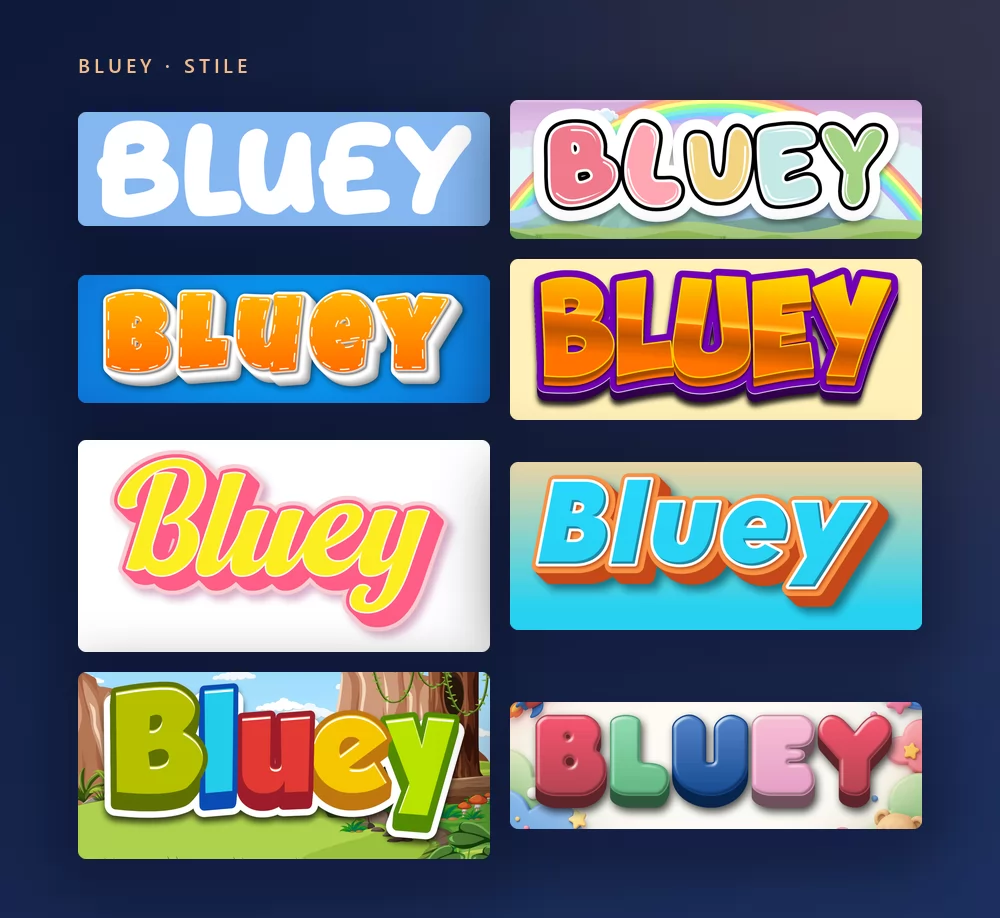
Alle stammen aus demselben Bluey-Schriftgenerator, nur mit einem anderen Stil aus der Liste. Nichts zu installieren, kein Konto.
Über die Bluey-Schrift
Bluey ist eine australische Zeichentrickserie für Vorschulkinder, erdacht von Joe Brumm und produziert von Ludo Studio in Brisbane. Sie lief 2018 zuerst auf ABC Kids und ging über BBC Studios und Disney+ um die Welt. Sie folgt Bluey, einem sechsjährigen Blue-Heeler-Welpen, ihrer kleinen Schwester Bingo und den Eltern Bandit und Chilli durch Fantasiespiele, die den zuschauenden Erwachsenen jedes Mal eine Lebensweisheit unterjubeln.
Das Logo der Serie ist ein eigens gezeichneter Schriftzug: dicke, runde, hüpfende Versalien, die für die Sendung entworfen und nie als Schrift veröffentlicht wurden. Die Schrift für alles andere, die Titelkarte, den Abspann und die offizielle Website, ist Hello Headline, entworfen von Veneta Rangelova und bei DearType erschienen. Als 2023 Bluey: The Videogame kam, stand auch „The Videogame" unter dem Logo in Hello Headline. Es ist eine kommerzielle Schrift.
Für kostenlose Schriften mit ähnlichem Look nennen die Seiten, die auf diese Suche ranken, alle dieselben drei: Blue Custard von rockcake sowie Lovely Bubbles und Magical Markers von Darrell Flood. Heyam von FG Studios ist die andere nahe kommerzielle Entsprechung.
Bluey-Text erstellen
Schritt 1. Den Namen eintippen
Öffne den Generator und ersetze den Beispieltext durch deinen eigenen: den Namen eines Kindes, „Alles Gute zum Geburtstag", ein Klassenschild. Die Buchstaben werden beim Tippen neu gezeichnet. Der Stil setzt alles von selbst in Versalien, so wie das Logo.
Schritt 2. Einen Stil wählen
Der Klassiker sind dicke weiße runde Versalien auf Himmelblau. Im Tab Stile lassen sich Füllung, Kontur und Schatten getrennt ändern, du behältst also die hüpfenden Buchstabenformen und nimmst die Farben woandershin: Orange für eine Bingo-Party, ein blasses Rosa, ein Regenbogen.
Schritt 3. Das Format wählen
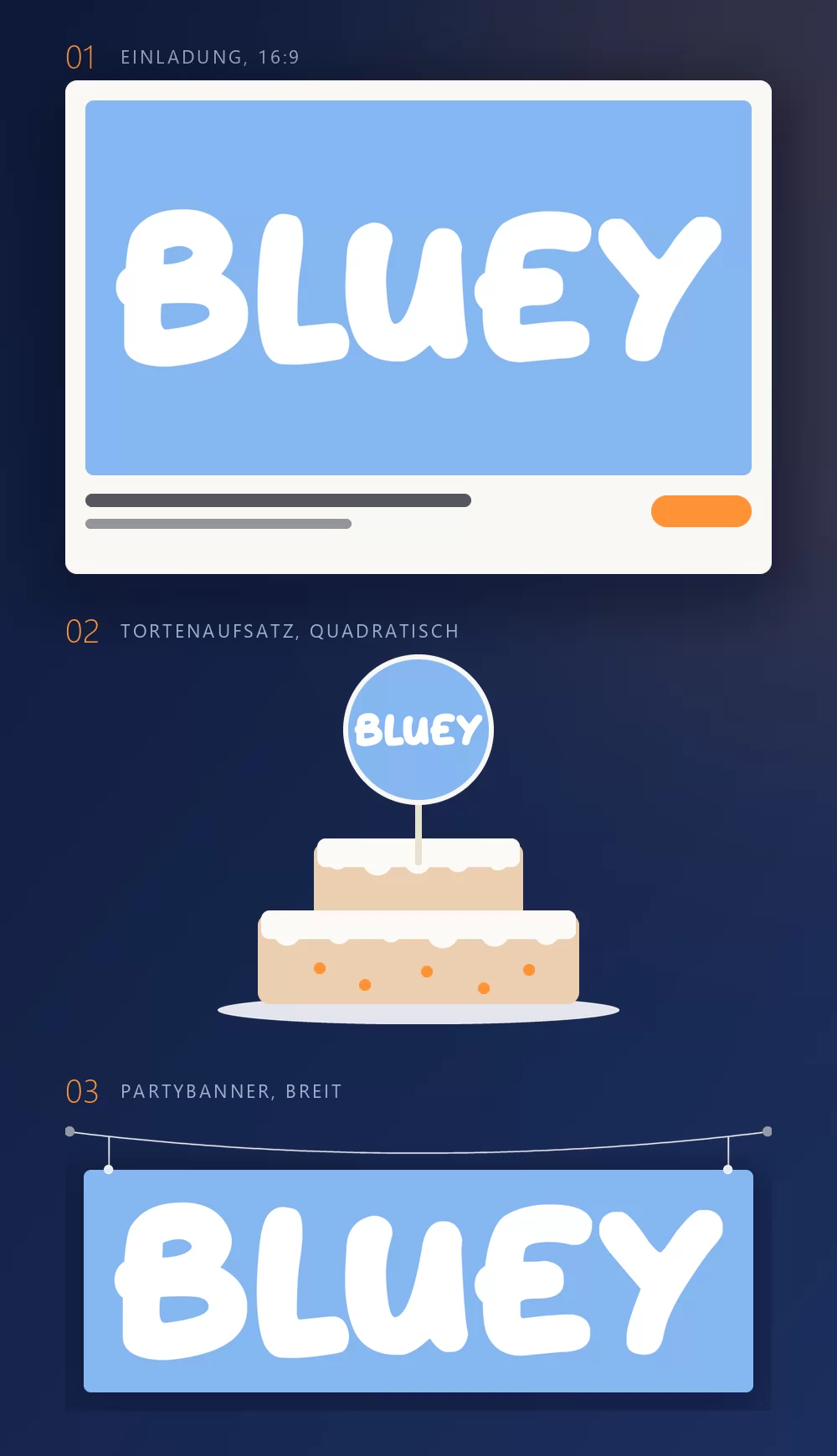
Stell das Format vor dem Export ein, dann wird später nichts beschnitten. 16:9 für eine Einladung, ein Quadrat für einen Tortenaufsatz oder einen Cupcake-Picker, ein breiter Streifen für ein Banner quer über die Wand. Die drei Mock-ups oben zeigen, was aus diesen Formaten wird, sobald sie gedruckt sind.
Schritt 4. Herunterladen
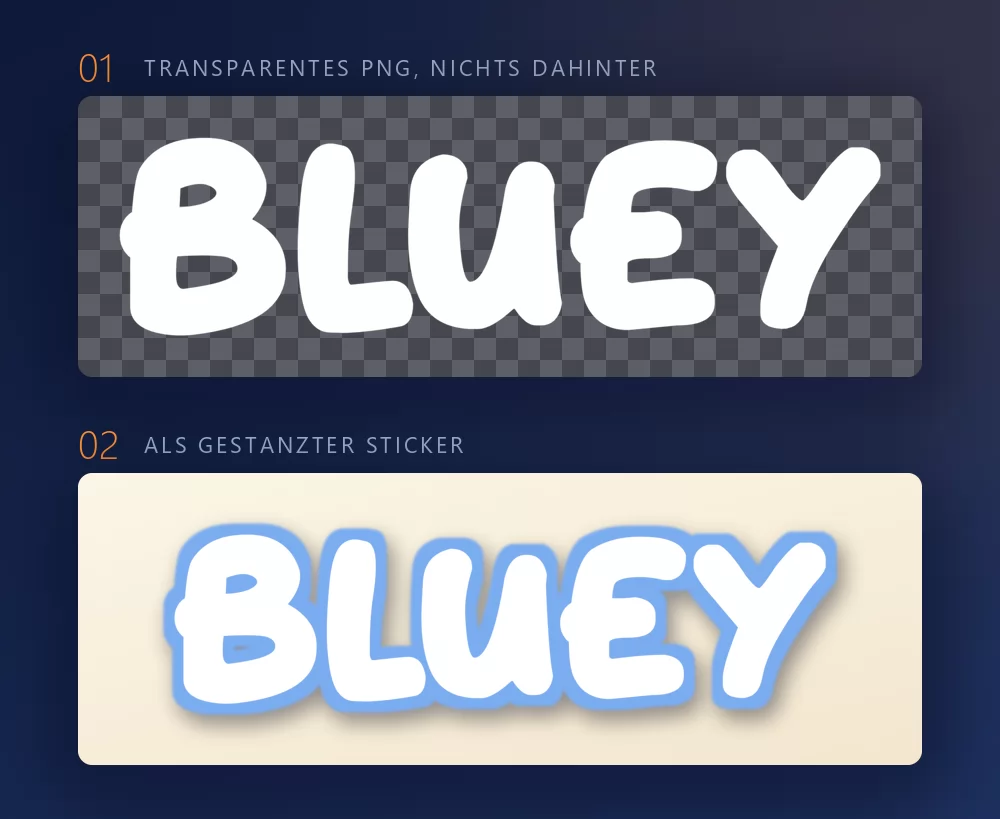
Nimm im Tab Download das transparente PNG, wenn du den Namen auf dein eigenes Design setzen willst. Diese Option übersehen die meisten, und für Party-Drucksachen ist sie die entscheidende: dein eigenes Papier, der Name darüber, kein blauer Kasten drum herum. Es ist auch das, was ein Schneideplotter für einen gestanzten Sticker oder Topper braucht: Die Form der Buchstaben ist die Form des Schnitts.
Lange Namen füllen die Breite schnell
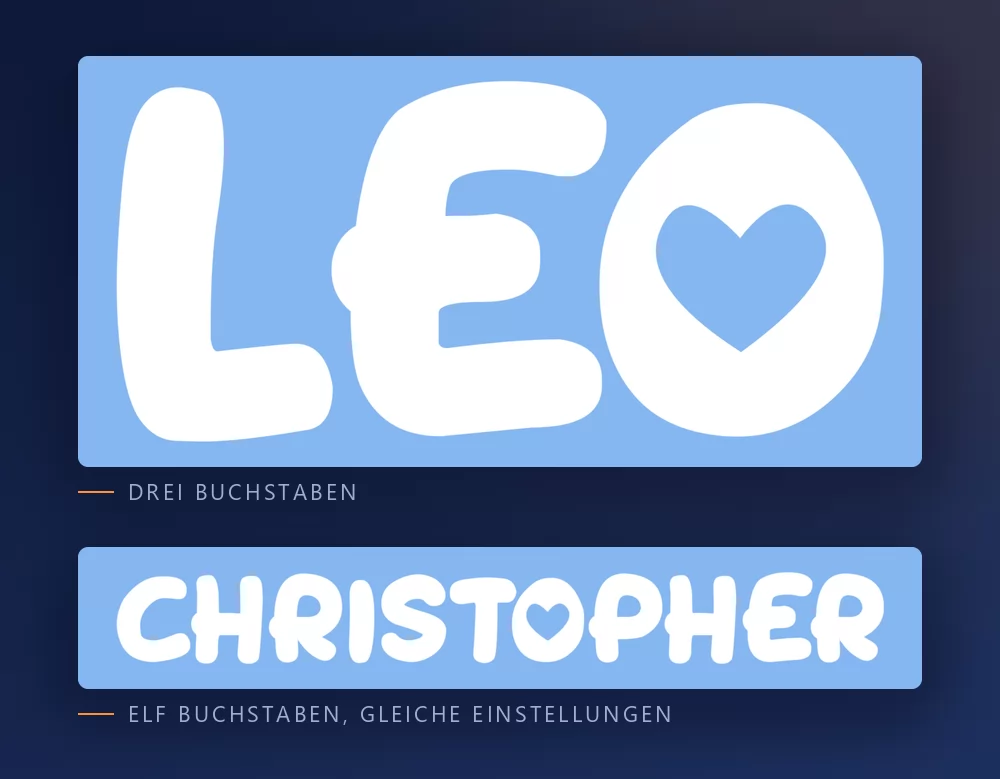
Je mehr Buchstaben, desto enger sitzen sie. Der Zeichenabstand ist ein Regler im Tab Text: etwas öffnen, und ein langer Name wirkt nicht mehr gequetscht. Derselbe Tab enthält Zoom, Zeilenhöhe, Bogen und Drehung.
Der Bluey-Look oder der Spielzimmer-Look
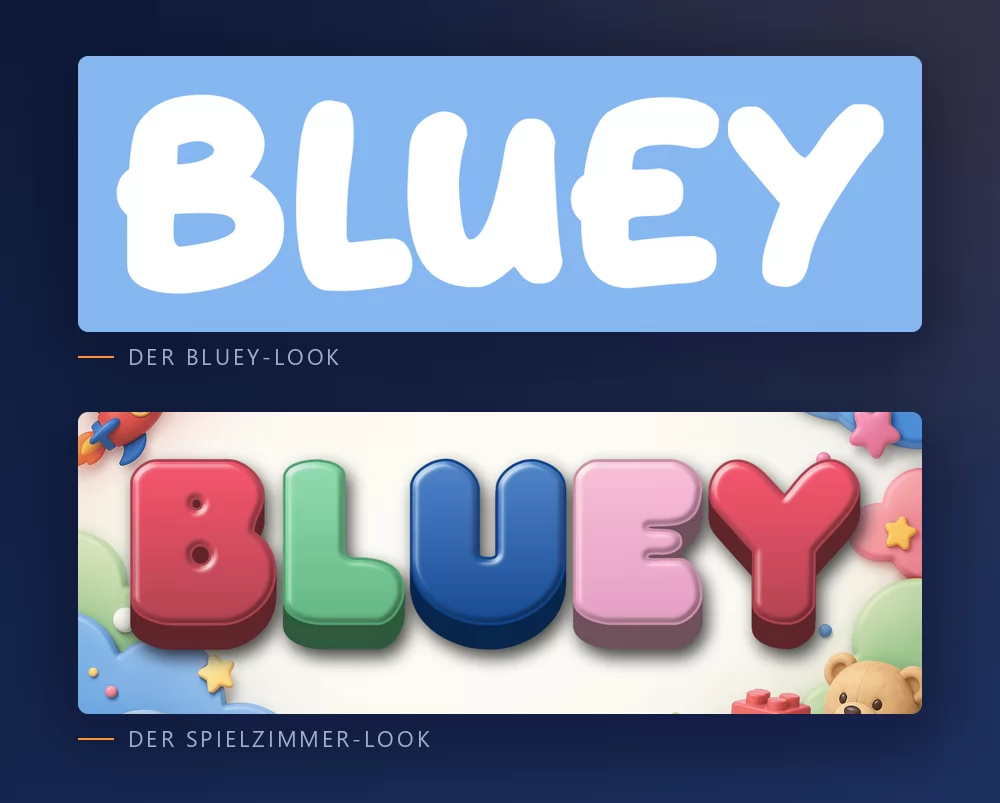
Der Bluey-Look ist das Logo selbst: weiß, dick, rund, ein bisschen hüpfend, auf diesem Himmelblau. Das haben die meisten im Kopf, und das braucht ein Bluey-Geburtstag.
Der Spielzimmer-Look sind runde Plastikbuchstaben in Pastellfarben mit Spielzeug drum herum. Er trägt kein Serienbranding, was ihn zur besseren Wahl für eine Kinderzimmerwand oder einen ersten Geburtstag ohne Motto macht. Der Spielzimmer-Buchstabengenerator hat ihn als Voreinstellung.
Welche Schrift, wenn du eine installieren willst
Das Logo selbst ist keine Schrift. Es ist ein eigens gezeichneter Schriftzug, also ist jede Datei namens „Bluey-Schrift" jemandes Nachbildung davon.
Hello Headline ist die echte Antwort für den Rest der Serie. Eine kommerzielle Schrift von DearType, gekauft und heruntergeladen bei der Schriftschmiede. Wer genau den Look von Titelkarte und Abspann will, braucht diese.
Blue Custard von rockcake ist die kostenlose Schrift, die den hüpfenden Versalien des Logos am nächsten kommt. Sie liegt auf DaFont als Donationware: frei nutzbar, eine Spende an den Designer willkommen.
Lovely Bubbles und Magical Markers, beide von Darrell Flood, sind die zwei anderen, die jede Liste nennt. Lovely Bubbles ist als kostenlos für den privaten Gebrauch gelistet, Magical Markers als Donationware, beide auf DaFont.
Für Kundenarbeit, wo die Lizenz sauber sein muss, sind die ehrlichen Optionen die runden Schriften mit offener Lizenz auf Google Fonts: Fredoka, im Geist am nächsten, mit einer ganzen Reihe von Schnitten, Baloo 2 und Sniglet. Keine davon ist eine Bluey-Schrift. Alle drei geben dir den freundlichen runden Look mit einer Lizenz, die niemand anzweifeln kann, und sie stehen in Canva bereit.
Was die Leute wirklich damit machen
Die Downloadseiten listen „beste Verwendungen", und sie passen zu dem, was tatsächlich entsteht: Geburtstagseinladungen, Torten- und Cupcake-Topper, Banner quer über die Wand, Namensschilder für eine Party, ein Shirt fürs Geburtstagskind, Klassenschilder und Willkommensschilder. Fast alles davon wird gedruckt, und fast alles funktioniert mit dem transparenten PNG besser als mit einer installierten Schrift, weil der Look die weißen Buchstaben auf genau diesem Himmelblau ist und eine Schriftdatei nur die Umrisse liefert.
Warum sieht mein Text neben dem echten Logo falsch aus? Meist wegen des Blaus, nicht wegen der Schrift. Das Logo sitzt auf einem hellen, leicht vergrauten Himmelblau. Auf einem knalligen Elektroblau, oder mit einem Verlauf, liest es sich nicht mehr als Bluey.